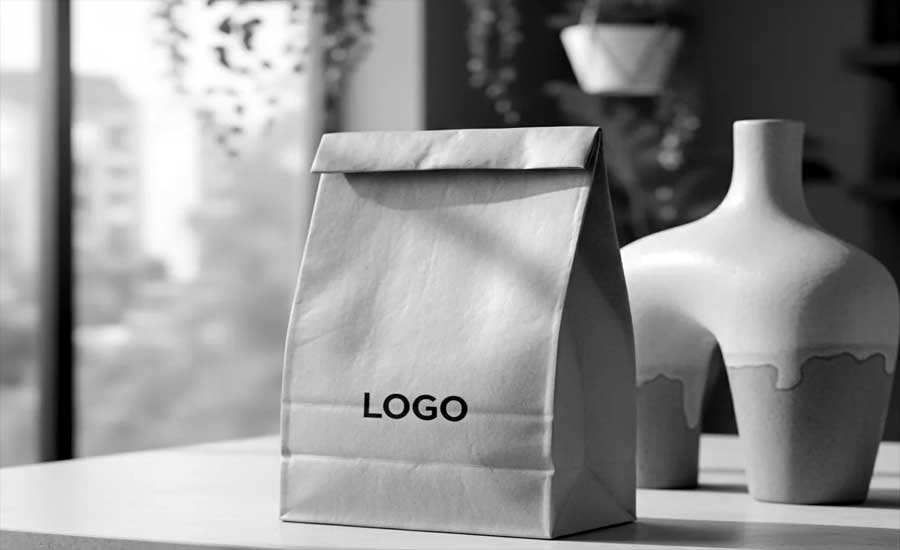
Когда вы заказываете бумажные пакеты на заказ, важно продумать не только материал и форму, но и то, как будет выглядеть ваш логотип и текст. Крафтовая бумага имеет особенную текстуру и цвет, поэтому далеко не каждый шрифт на ней работает одинаково хорошо.
Некоторые начертания подчёркивают натуральность и стиль бренда, а другие полностью теряются на коричневом фоне.
В этой статье разберёмся подробно, как правильно подбирать шрифты для крафт пакетов, чтобы ваш бренд выглядел выгодно и профессионально.
Особенности крафт бумаги и её влияние на восприятие шрифта
Крафт бумага отличается естественной текстурой, небольшими неровностями и тёплым коричневым оттенком. Это не гладкий белый картон, где видна каждая линия. На крафте мелкие детали могут сливаться, а тонкие линии становятся менее заметными. Поэтому при изготовлении бумажных пакетов из крафт бумаги важно выбирать шрифты с достаточной толщиной линий и хорошим контрастом.
Если вы планируете купить крафт пакеты оптом, подумайте заранее о дизайне. Светлые тонкие шрифты на крафте часто пропадают, особенно при печати в один цвет. Более жирные и контрастные начертания, наоборот, выглядят выразительно и легко читаются даже на расстоянии.
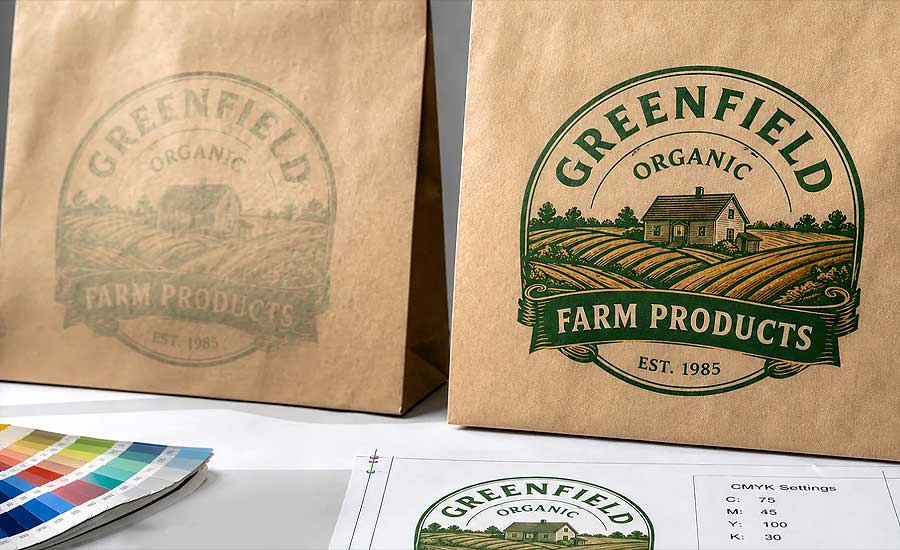
Какие шрифты лучше всего работают на крафт пакетах
На крафтовой бумаге отлично проявляют себя шрифты с выраженным характером. Классические рубленые (sans-serif) начертания средней и большой толщины показывают себя надёжно. Они хорошо читаются, подчёркивают современность бренда и не теряются на текстуре бумаги.
Для продуктовых магазинов, пекарен и кофеен часто выбирают шрифты с лёгким рукописным стилем, но не слишком тонкие. Такие начертания передают теплоту и натуральность, что прекрасно сочетается с крафт материалом. Главное — чтобы буквы имели достаточный вес и расстояние между символами.
Почему жирные и полужирные шрифты выигрывают на крафте
Жирное начертание создаёт необходимый контраст с натуральным цветом крафт бумаги. Даже если пакет лежит на столе среди других товаров, логотип остаётся заметным. Это особенно важно для брендированных бумажных пакетов на заказ, которые работают как мобильная реклама вашего бизнеса.
С засечками или без: что выбрать для крафт пакетов
Шрифты с засечками (serif) придают упаковке классический, премиальный вид. Они хорошо подходят для брендов, которые хотят подчеркнуть традиции и качество. Однако на крафте засечки должны быть достаточно крупными, иначе они могут слиться с текстурой.
Рубленые шрифты без засечек чаще выбирают современные кафе, службы доставки и магазины здорового питания. Они выглядят чисто и минималистично, что важно для быстрого восприятия информации.
Шрифты, которые часто теряются на крафт бумаге
Тонкие, светлые и декоративные шрифты с множеством завитушек плохо подходят для крафт пакетов. На текстурированной поверхности мелкие элементы размываются, а тонкие линии могут не пропечататься полностью. В результате надпись становится нечитаемой.
Особенно рискованно использовать такие шрифты на маленьких пакетах или когда текст занимает мало места. При изготовлении пакетов с окном или пакетов без ручек важно, чтобы вся важная информация была хорошо видна.
Типичные ошибки при выборе шрифта для упаковки
Многие предприниматели выбирают красивый шрифт, который нравится им на экране компьютера, но забывают проверить его на реальном крафт материале. В результате после печати бумажных пакетов с логотипом приходится переделывать тираж.
- Слишком тонкие линии, которые теряются на текстуре
- Очень мелкий размер шрифта
- Сложные декоративные начертания с множеством деталей
- Светлый цвет печати без достаточного контраста
- Слишком большое расстояние между буквами
Практические рекомендации по дизайну бумажных пакетов
При заказе крафт пакетов с ручками или пакетов с прямоугольным дном важно учитывать размер самой упаковки. На больших пакетах можно позволить себе чуть более сложные шрифты, а на маленьких — только максимально читаемые.